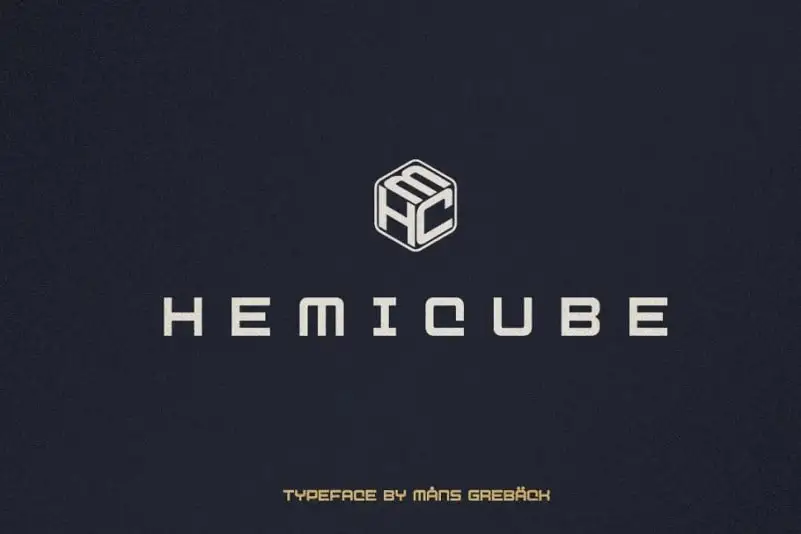
A Hemicube Sans Serif é uma nova adição à família de fontes de séries, criada pelo talentoso designer Mans Greback. Inspirada nas nuances geometricamente fortes e desafiadoras do design futurista, esta fonte apresenta uma elegância minimalista e limpa que a torna perfeitamente adaptável para ambientes gráficos no contexto da ciência-ficção ou tecnologia. Seja você um designer de logotipos, ilustrador ou mesmo o criador do próximo game de realidade virtual, Hemicube pode ser sua fonte ideal, oferecendo uma combinação única e inovadora que ajuda a criar designs profundos e envolventes. Esta elegante fonte apresenta um estilo clean, mas repleto de sutis nuances, tornando-a perfeita para estilos gráficos futuristas ou tecnológicos, enquanto ainda permite uma personalização suave que tornará suas criações únicas.